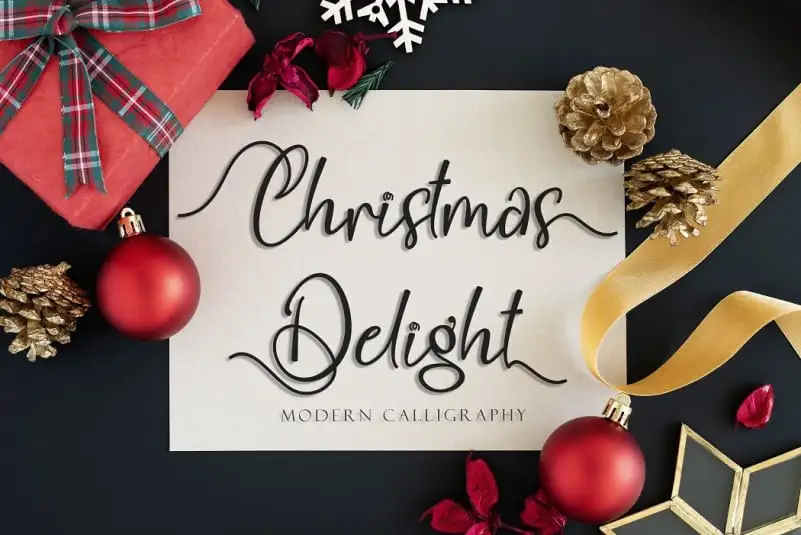
Christmas Delight Calligraphy Font – Download Grátis
Esta fonte ‘Christmas Delight Calligraphy Font’ é uma criação única e cheia de bom humor, especialmente projetada para celebrar a chegada do Natal. Ela é perfeita para criar cartas de felicidade natalinas, frases inspiradoras, posts em redes sociais sobre o Natal, promoções, saudações para os aniversários, bens matrimoniais e até mesmo anúncios de casamentos ou eventos especiais. Como uma fonte script, ela adicionará um toque especial a qualquer projeto natalino que você estiver criando. Seja você um designer gráfico profissional ou simplesmente alguém que gosta de decorar o seu Natal com cuidado e arte, esta fonte é perfeita para quem deseja adicionar um brilho festivo à sua decoração e a seus projetos digitais natalinos.